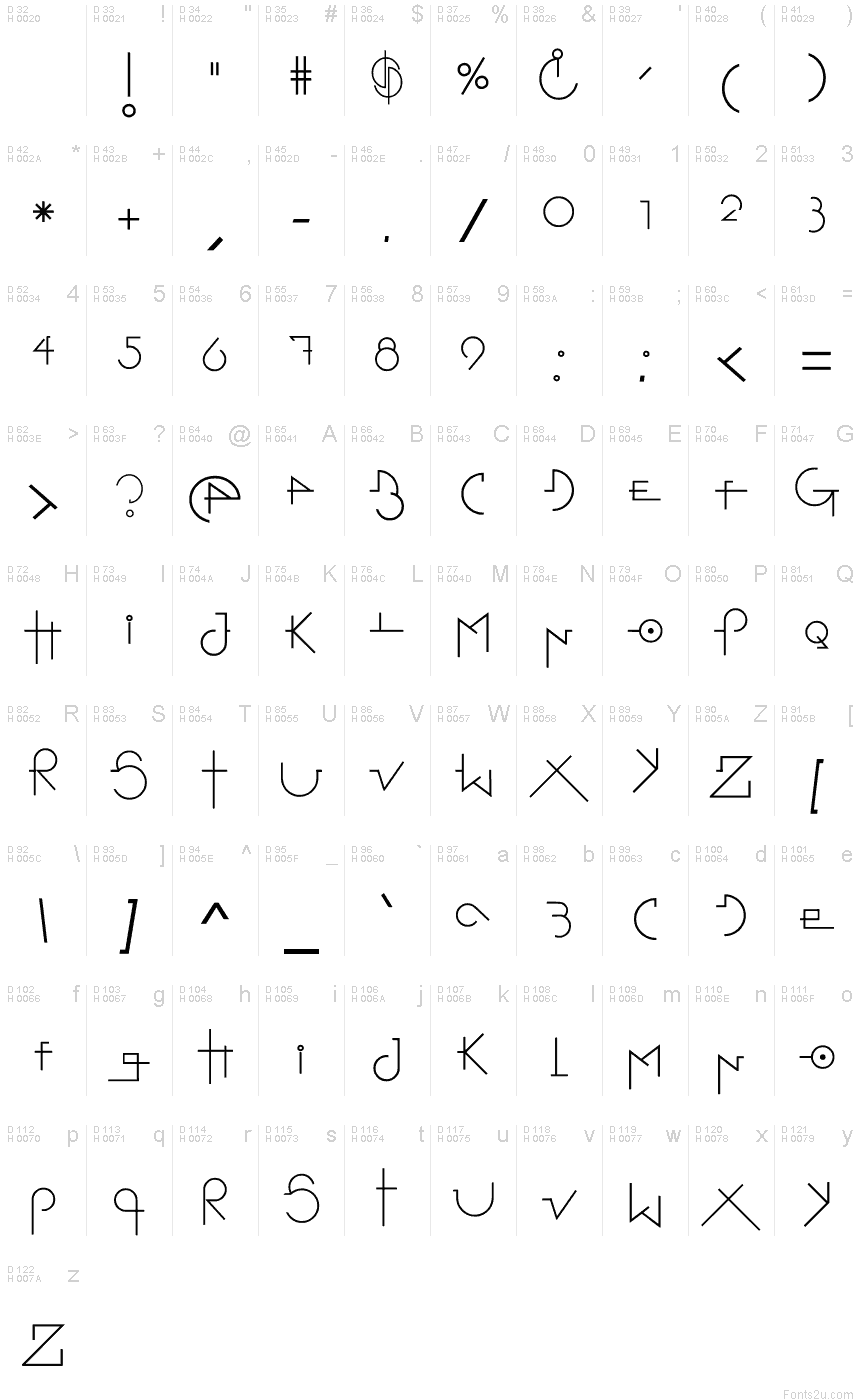
Stretched Signature Flex, jehož autorem je Galdino Otten, je bezplatné futuristické monoline displejové písmo s extrémně vysokými tahy a širokými kruhovými křivkami. Vlasová konstrukce a rázné příčné tahy dodávají písmenům architektonický a schematický charakter.
Designéři působící v oblasti technologií a experimentální kultury jej mohou využít na plakáty akcí, obaly alb, digitální grafiku a módní branding. Prodloužené linie mohou připomínat cesty obvodů, mapové sítě nebo schematické ilustrace a proměnit tak nadpis v součást okolního obrazu.
This font was conceived according my self signature that you can see in all my artwork in my blog as well street art writings, and the it can be used in diverses ways and artstylles, it can be used of the simplest the most sophisticated work until. Its more important characteristic is the flexibility of its connections, for being linked becomes infinitely flexible being able to transpose the limitations of any space.